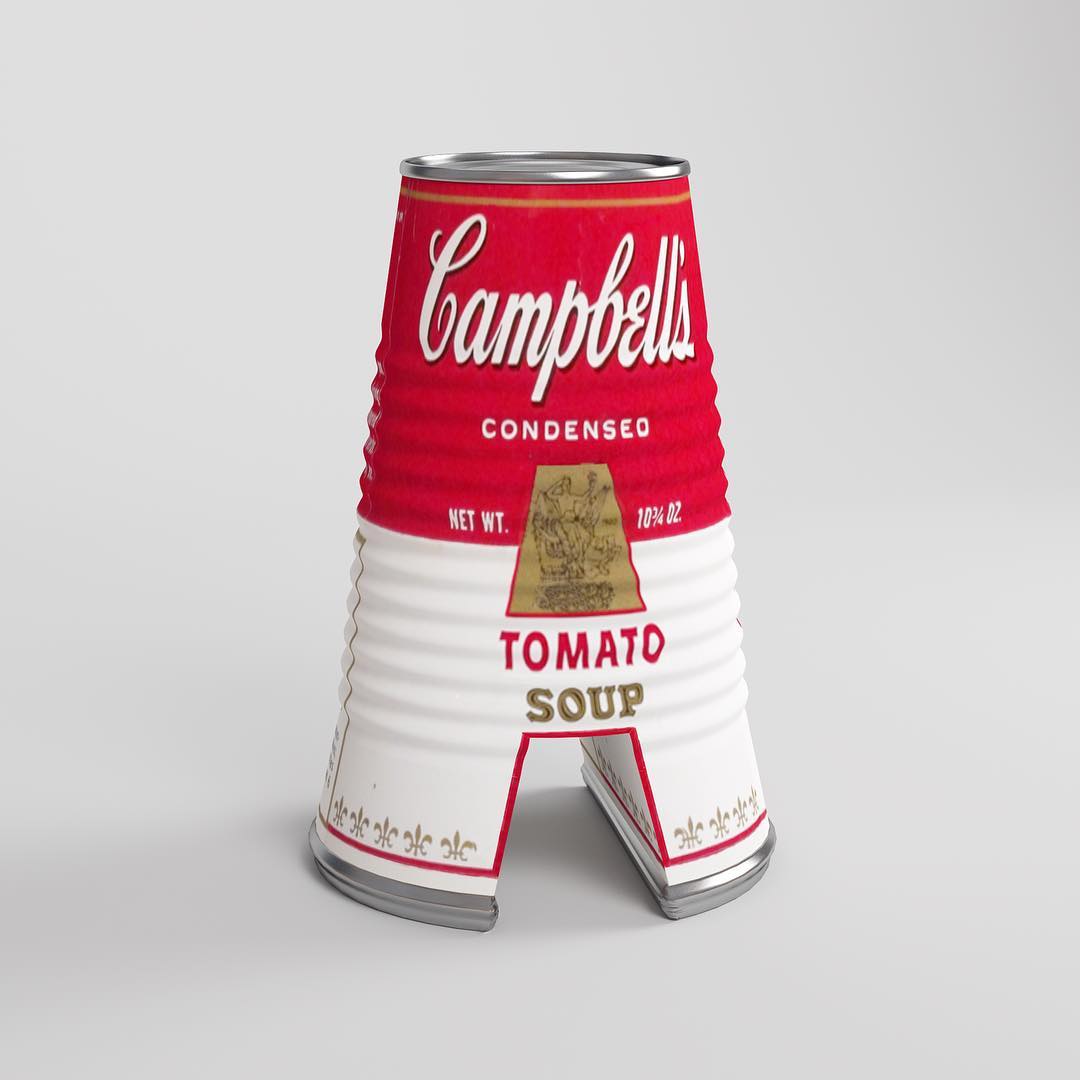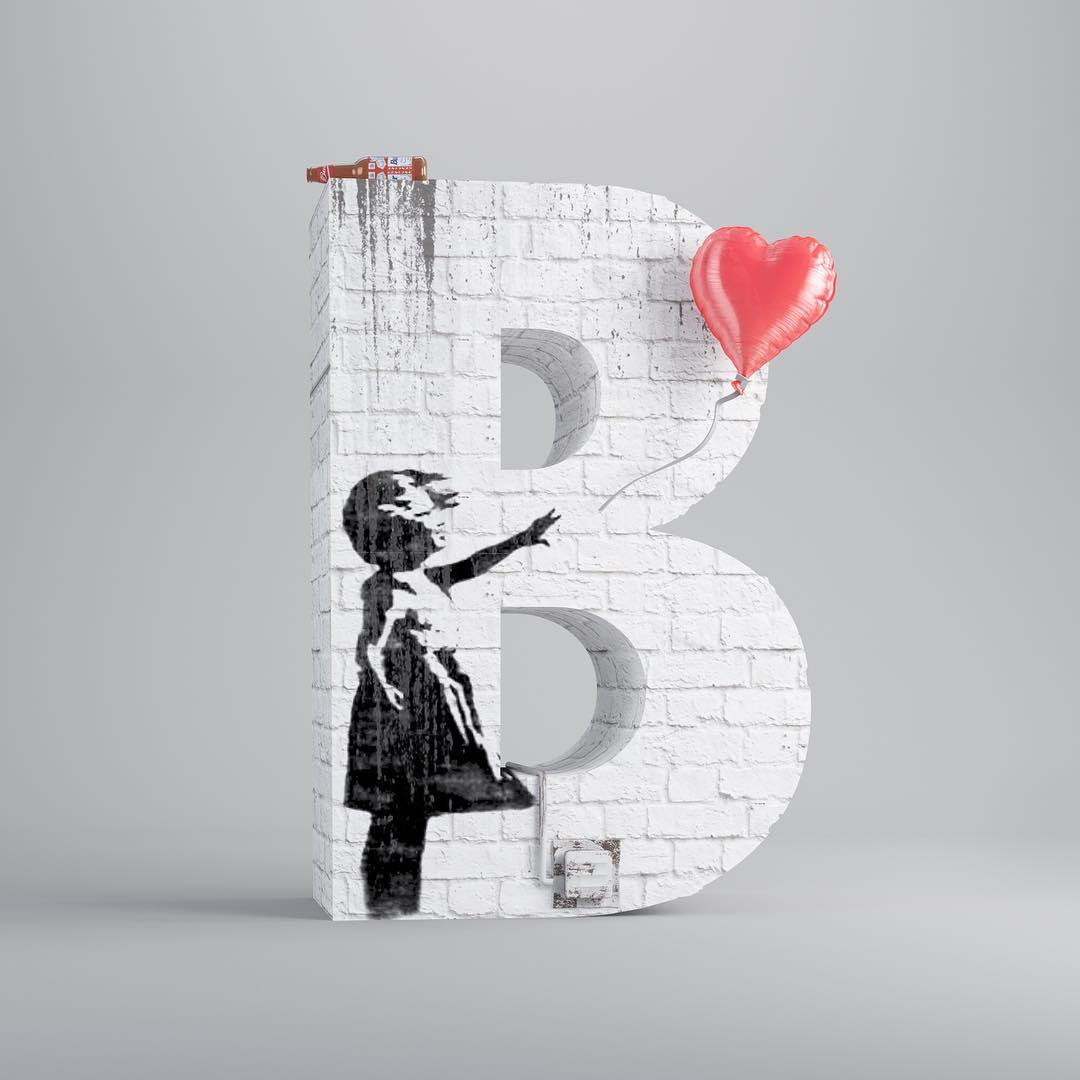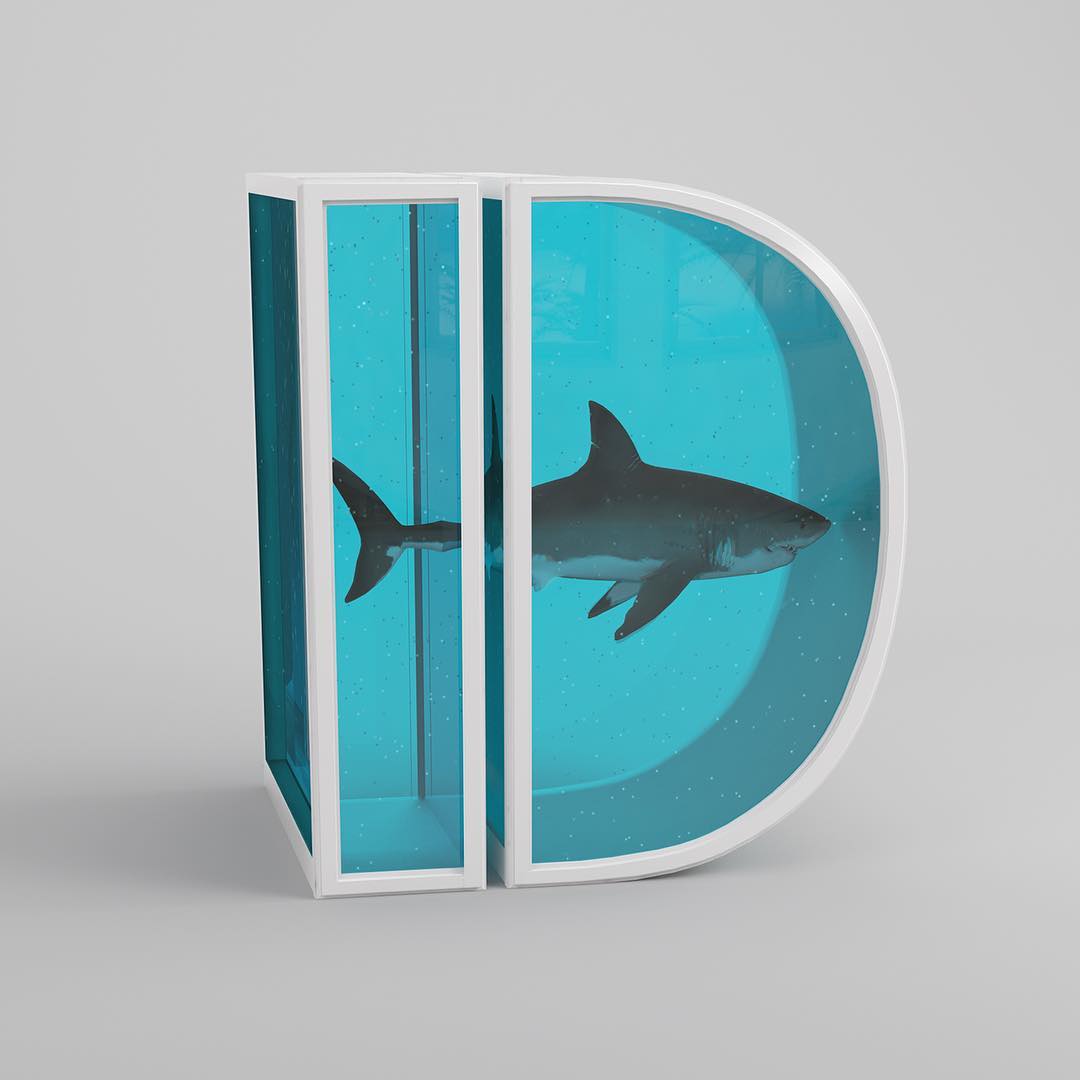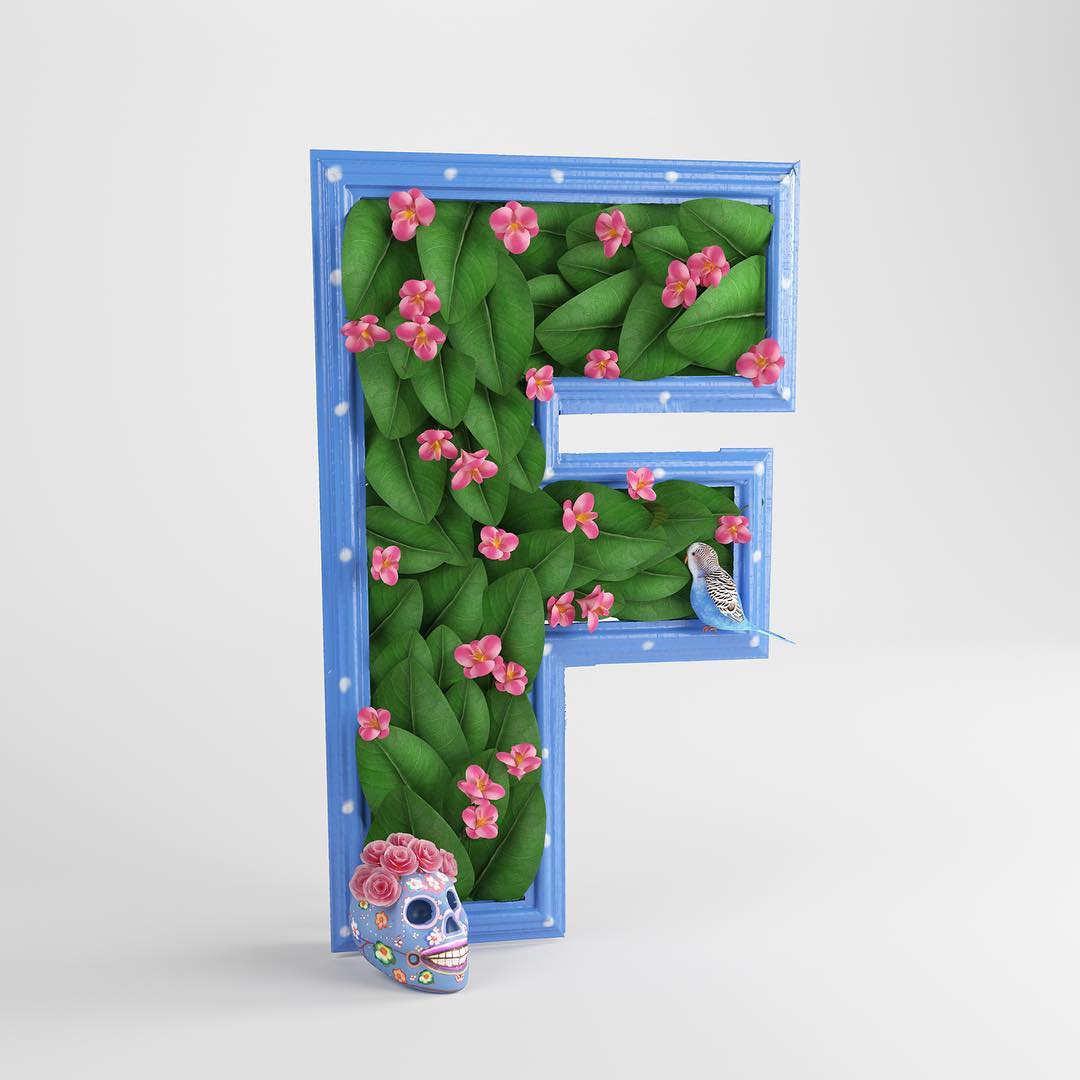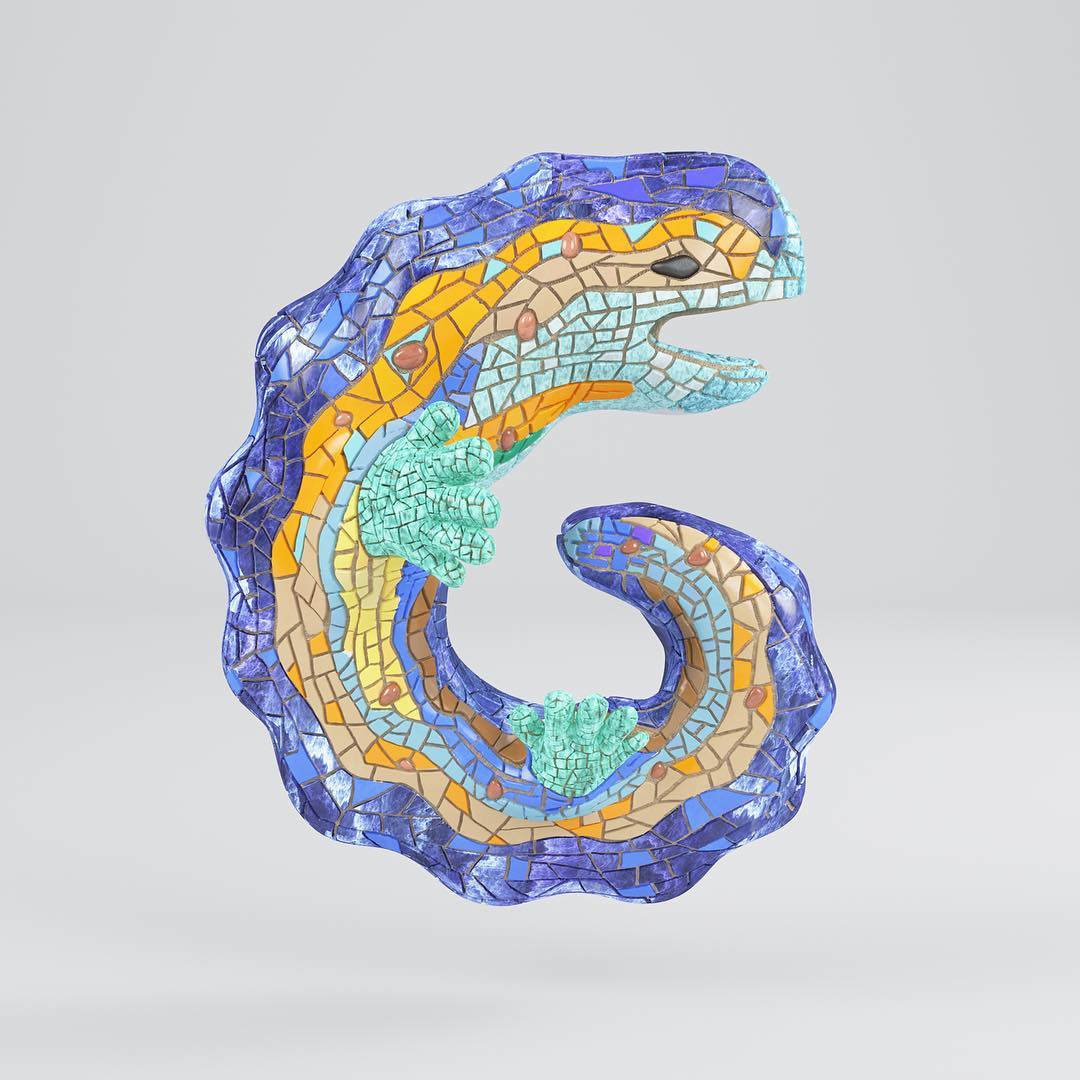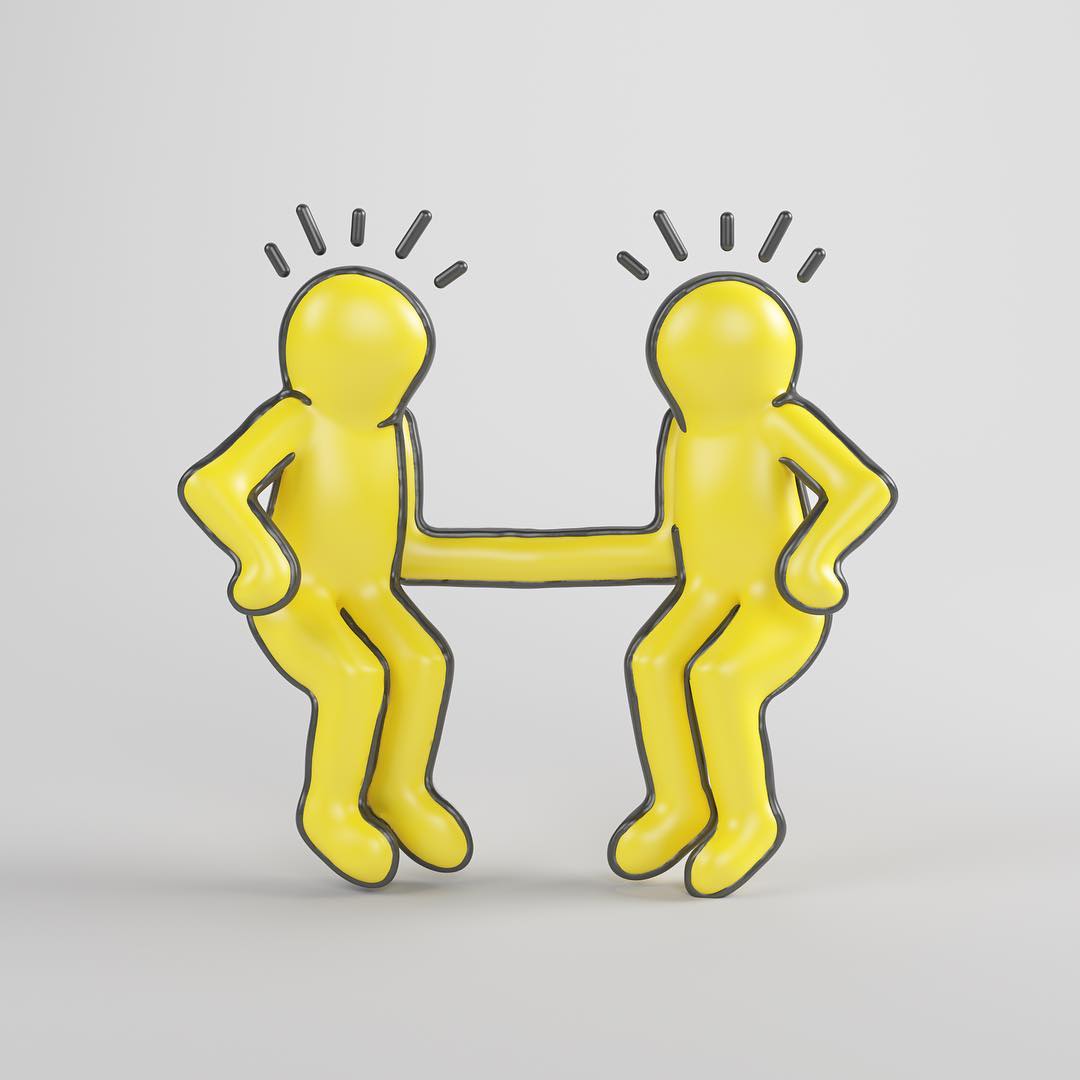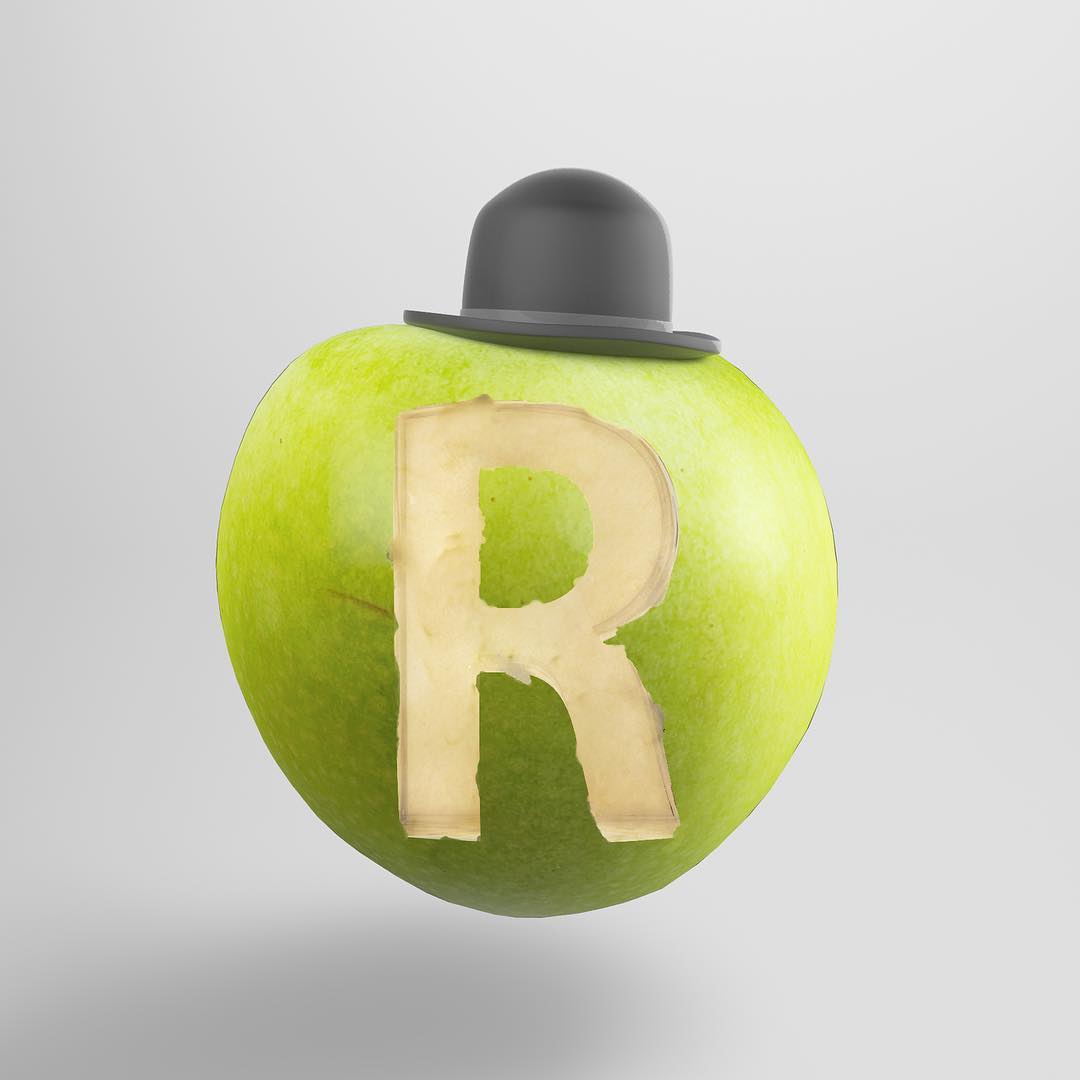
Испанская студия выпустила шрифт в стилистике известных произведений искусства
Азбука искусства
Испанская студия CESS создала шрифт Artphabet, вдохновленный произведениями искусства. Каждая буква посвящена стилистике работ известных художников.
Авторы проекта, как правило, использовали ссылки на искусство XX и XXI веков — в алфавите можно найти Пита Мондриана, Василия Кандинского, Тома Вессельмана, Сальвадора Дали, Энди Уорхола, Такаси Мураками, Джеффа Кунса и других художников.
Пока шрифт представлен в виде 3D-иллюстраций. Однако дизайнеры рассказали, что скоро Artphabet может быть издан в виде небольшой книги.